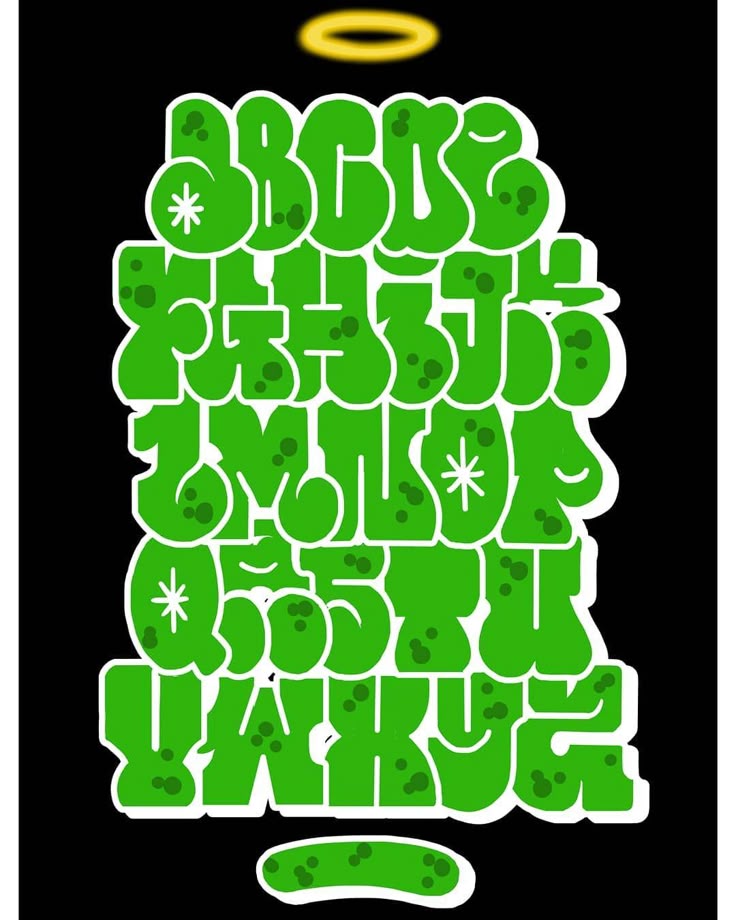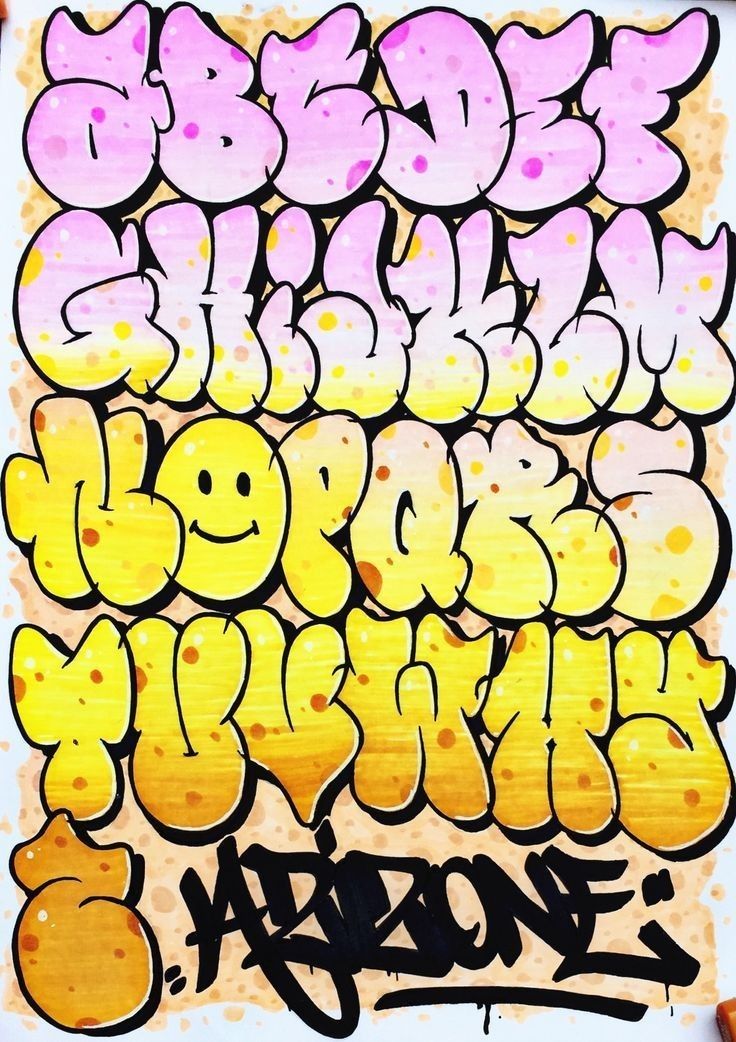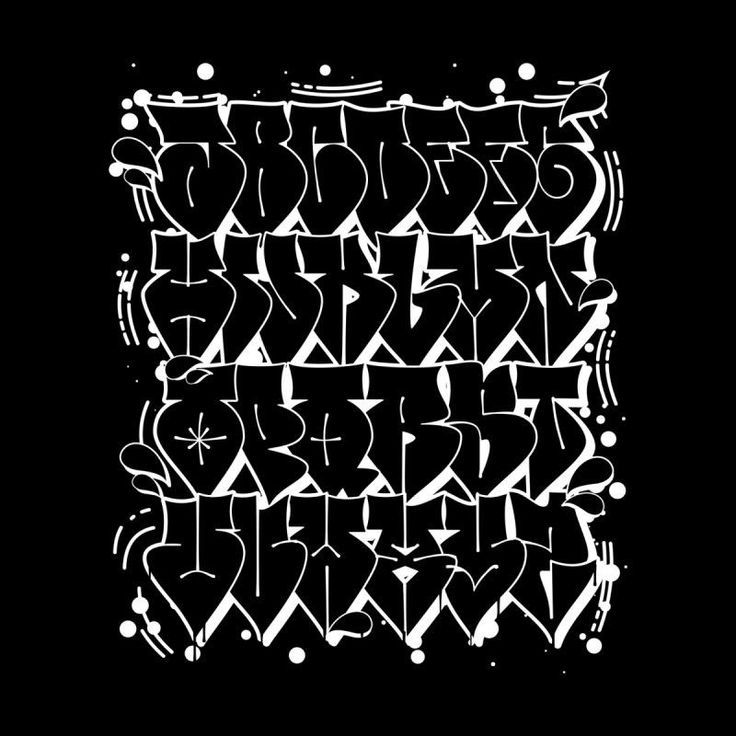
28 лучших шрифтов граффити для городского дизайна
Шрифты граффити идеально подходят для уличного искусства, наклеек и любого другого дизайна, в котором вы пытаетесь создать эклектичную городскую эстетику.
Они мощные, резкие и полные индивидуальности.
Чтобы помочь вам найти идеальный шрифт для ваших проектов в уличном стиле, мы составили список лучших граффити-шрифтов на рынке.
Мы тщательно отобрали этот список и позаботились о том, чтобы в него вошли только самые лучшие шрифты от лучших дизайнеров. Существует сочетание бесплатных и премиальных вариантов, поэтому вы сможете найти то, что соответствует вашему проекту и бюджету.
Что такое граффити-шрифты?
Шрифты Graffiti — это шрифты, вдохновленные уличным искусством. Они дерзкие, громкие и характерные, и обычно выглядят так, как будто их поцарапали, нацарапали или распылили на поверхность.
Существует множество различных типов шрифтов для граффити, но некоторые из самых популярных включают:
- Трафаретные шрифты . Они пытаются воссоздать вид, который вы получите, рисуя граффити распылением по трафарету. Вспомните Бэнкси.
- Накидные купели. Это шрифты, похожие на теги, которые обычно состоят из пузырьковых букв.
- Шрифты Wildstyle . Wildstyle — сложный, замысловатый стиль граффити. Эти типы шрифтов, как правило, трудно читаемы и сильно стилизованы.
- Капающие купели . Этот стиль шрифта граффити имеет формы букв, которые выглядят так, как будто с них капает краска.
- Шрифты кисти . Это шрифты, которые пытаются имитировать мазки кисти
- Начертанные шрифты . Этот тип граффити-шрифта выглядит так, как будто он был грубо и небрежно написан ручкой или карандашом, как если бы вы рисовали в блокноте.
В отличие от других типов шрифтов, шрифты Graffiti не предназначены для чтения. Они чисто художественные. Таким образом, они обычно не являются хорошим выбором для таких вещей, как заголовки или основной текст, но они очень художественны и могут отлично смотреться на плакатах, модных товарах и наклейках.
28 лучших граффити-шрифтов
1. Nightfate — наш лучший выбор
Nightfate, по рисунку, является самым популярным граффити-шрифтом на Envato Elements — и я понимаю, почему.
Он использует жирные, похожие на пузыри символы с сочетанием закругленных краев и острых углов и поставляется в форматах TTF, OTF и WOFF.
Почему это наш лучший выбор
В Nightfate есть все, что мы ищем, в граффити-шрифте. Он использует классический дизайн в стиле броска, который должен быть знаком всем, кто когда-либо жил в городской местности. Это универсальный шрифт, который не будет выглядеть неуместным на уличном искусстве, но также будет хорошо работать в дизайне одежды, настенных украшениях и наклейках, и даже логотипе.
2. Rollover
Rollover — это шрифт для граффити от Vunira. Эффект капель заставляет буквы выглядеть так, как будто они были распылены, а краска все еще влажная. Это также делает этот шрифт хорошим для дизайна на тему ужасов, так как в правильном цвете эффект капания может напомнить кровь.
Это может хорошо работать на обложках книг ужасов, наклейках и кинопостерах. Пакет шрифтов также содержит стилистические варианты, лигатуры и росчерки.
3. Throw-up Font
Вот классный многослойный всплывающий шрифт от дизайнера Гаспера Муньоса. Дизайнер (имеющий опыт граффити) черпал вдохновение в культуре граффити, особенно в «бомбах» и «флопах» — подвидах граффити, которые можно создать быстро и которые известны своими простыми формами.
Флопы и бомбы обычно изготавливаются с помощью аэрозольной краски и клапанов, позволяющих краске переходить от тонких к толстым мазкам, и Гаспер попытался отразить это в своем шрифте. Разве вам не нравятся эти милые округлые формы букв?
Пакет шрифтов поставляется в четырех версиях: обводка, заливка, тень и выделение. Эти различные варианты могут быть наложены друг на друга, чтобы создать привлекательный дизайн, который, кажется, спрыгивает со страницы.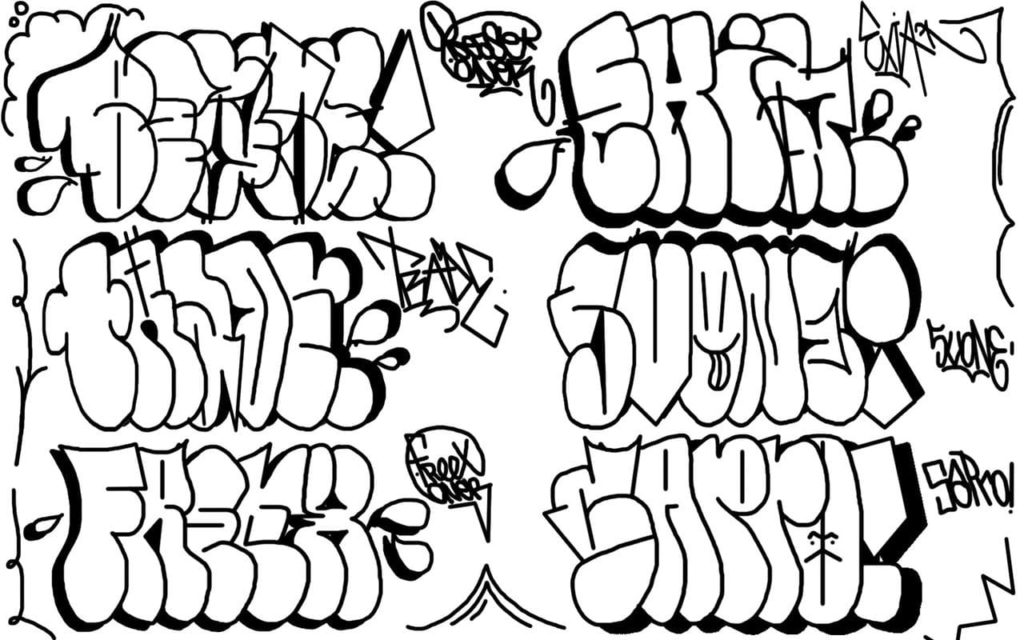
Цена: Бесплатно
Цена: Личное и коммерческое использование включено в подписку на Envato Elements (16,50 долларов США в месяц)
4. Он вдохновлен уличным искусством и напоминает мне о тегах, которые можно увидеть на кирпичной стене. Это будет хорошо работать с дизайном в стиле хип-хоп, уличной одеждой и настенным искусством. Он поставляется с заглавными буквами, знаками препинания и цифрами в формате OTF и TTF.
Цена: Личное и коммерческое использование, включенное в подписку Envato Elements ($16,50/месяц)
5. Luser
Luser — это шрифт современного уличного искусства, вдохновленный культурой хип-хопа и граффити. Он имеет плавные мазки, которые выглядят круто, и это один из самых читаемых граффити-шрифтов в этом списке, поэтому он может хорошо работать в заголовках.
Цена: Личное и коммерческое использование, включенное в подписку на Envato Elements (16,50 долларов США в месяц)
6.
Bombsky
Забудьте о Бэнкси, позвольте представить вам Bombsky — граффити-шрифт от Blankids. Как следует из названия, дизайн основан на классических граффити-бомбах (напоминаем: бомбы — это простые граффити-ярлыки, которые можно быстро сбросить). Я вижу, как это выглядит очень красиво на обложке хип-хоп альбома.
Цена: Личное и коммерческое использование, включенное в подписку Envato Elements ($16,50/месяц)
7. Punk Kid
Освободите свой внутренний панк с помощью этого бесплатного трафаретного шрифта в стиле граффити от Криса Хансена. Punk Kid отличается от других шрифтов, которые мы рассматривали до сих пор, тем, что он использует классический стиль трафарета с аккуратными однородными формами букв. Подобно трафаретным буквам, на лице каждого глифа есть разрывы.
Что отличает Punk Kid от классических трафаретных шрифтов, так это крутая размытая текстура и крапчатый эффект, из-за которых он выглядит так, как будто его небрежно распылили в спешке.
Это очень бунтарский шрифт, который будет отлично смотреться на дизайнах обид, веб-сайтах групп, обложках альбомов, концертных афишах и многом другом.
Этот шрифт широко доступен бесплатно даже для коммерческого использования. Но если вы хотите выразить свою благодарность, дизайнер предлагает вам сделать пожертвование в больницу для коал в Новом Южном Уэльсе.
Цена: Бесплатно
8. Beslyn
Beslyn — изящный, изысканный шрифт в стиле граффити от Skiiler Studio. Элегантный стиль хорошо подходит для более серьезного, профессионального или стильного дизайна и особенно хорошо смотрится на темном фоне. Это встроенный шрифт, что означает, что он имеет тонкую штриховую линию внутри каждой буквы, чтобы добавить контраста и визуального интереса.
Цена: Личное и коммерческое использование, включенное в подписку Envato Elements ($16,50/месяц)
9. Hosp
Hosp — это стильный каллиграфический шрифт от Nick Asphodel Design.
Дизайнер хотел «помочь творческим людям создавать впечатляющие дизайны» и создал Hosp вручную с помощью остроконечной кисти. Наклонные, угловатые формы букв, чернильные пятна и грубые мазки выглядят круто и создают мощную атмосферу. Этот вариант идеально подходит для дерзких дизайнов продуктов, принтов на кепках, наклеек и других городских дизайнов.
Цена: Бесплатно
10. Airneo
Airneo — еще один потрясающий граффити-шрифт, который заставляет меня думать о баскетбольных площадках, кроссовках и хип-хопе. Он использует забавный, интересный и смелый дизайн с интересными завитушками, такими как наконечники стрел на концах перекладин, чтобы добавить изюминку. Он содержит прописные и строчные буквы, цифры, знаки препинания и многоязычные глифы.
Цена: Личное и коммерческое использование, включенное в подписку на Envato Elements (16,50 долларов США в месяц)
11. Mind The Gap
Mind the Gap — еще один трафаретный шрифт, который может хорошо работать в дизайне, вдохновленном уличным искусством и граффити.
Дизайнер был вдохновлен отношениями любви и ненависти, которые у него были с его ежедневными поездками в Лондон (отсюда и название, которое должно быть знакомо всем, кто когда-либо ездил в метро).
Шрифт отражает индустриальный, утилитарный характер станций метро в больших городах. Он был сделан путем ручной вырезки буквенных трафаретов и окраски их распылением. Военный вид компенсируется преднамеренными несовершенствами, которые делают его почти грязным и привносят некоторую индивидуальность в то, что в противном случае было бы относительно скучным дизайном.
Цена: Личное и коммерческое использование, включенное в подписку Envato Elements ($16,50/месяц)
12. Road Rage
Road Rage — агрессивный граффити-шрифт от Youssef Habchi. Острые углы и текстурированные мазки добавляют эффектности и делают этот шрифт одним из самых дерзких в этом списке. Я злюсь, просто глядя на это.
Цена: Бесплатно
13.
Брэдуолл
Далее у нас есть граффити-шрифт Bradwall от Blankids. Тебе не кажется, что на скейтборде это будет выглядеть круто? Опять же, он использует знакомый стиль с округлыми пузырьковыми буквами. Он бывает двух видов: обычный и контурный.
Цена: Личное и коммерческое использование, включенное в подписку на Envato Elements (16,50 долларов США в месяц)
14. Insanity
Insanity — современный шрифт в стиле граффити с собственным уникальным чувством стиля, от TK студия. Дизайнер выбрал более тонкие штрихи вместо пузырьковых букв, которые вы часто видите в шрифтах в стиле броска, что делает этот шрифт немного более универсальным. Это хаотично, дико и чертовски гангстерски. Попробуйте это на своих плакатах, уличных журналах, обложках YouTube, миниатюрах и постах в социальных сетях.
Цена: Личное и коммерческое использование, включенное в подписку Envato Elements ($16,50/месяц)
15.
Шрифт Diediedie
Далее у нас есть кое-что немного другое. Diediedie — это самопровозглашенный «злой каракуль-шрифт, которому определенно нельзя доверять». Вместо мазков кистью или баллончика с краской он имитирует маниакальные, беспорядочные каракули, которые можно делать ручкой в блокноте.
Страшный и немного жестокий, что делает его идеальным шрифтом для ужастиков и обложек альбомов рок-музыки. Помимо всех обычных глифов, дизайнер также включил несколько изящных дингбатов (таких как пентаграмма и череп), которые вы можете использовать, чтобы оживить свои проекты.
Цена: Бесплатно
16. Snakehead
Snakehead — это шрифт, похожий на теги, который будет отлично смотреться в логотипах, уличной одежде, брендинге и других проектах. Это шрифт с заглавными буквами, который содержит буквы от A до Z, цифры и знаки препинания, а также различные альтернативы и росчерки.
Цена: Личное и коммерческое использование, включенное в подписку на Envato Elements (16,50 долларов в месяц)
17. Flim Flom
Наполните свои проекты эстетикой ручной работы с Flim Flom от Maulana Creative. Это очень декоративный шрифт, который выглядит так, будто его нарисовали маркером или фломастером. Небольшие штрихи, такие как замена названия букв, таких как i и j, крестиками, добавляют визуального интереса и делают этот шрифт одним из самых оригинальных в этом списке.
Цена: Личное и коммерческое использование, включенное в подписку на Envato Elements (16,50 долларов в месяц)
18. Degrassi Font
Degrassi — это дурацкий шрифт, вдохновленный граффити, с волнистыми линиями и штрихами, заканчивающимися наконечниками стрел. Он доступен бесплатно и хорошо подходит для игровой графики, футболок, логотипов, постеров и многого другого.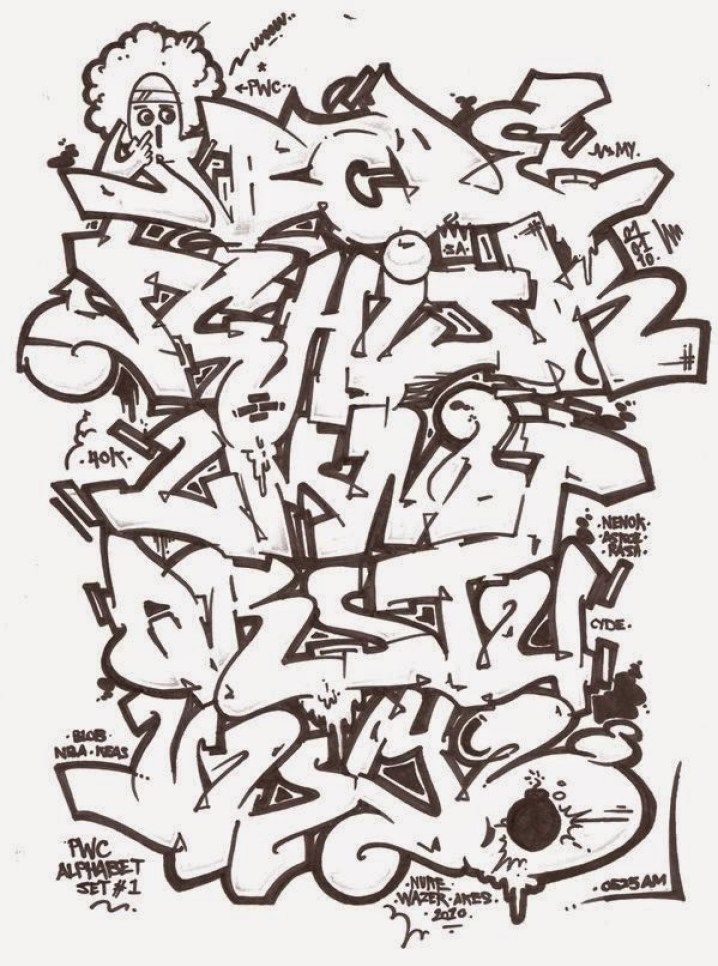
Цена: Бесплатно
19. MWD Graff
MWD Graff — шрифт для граффити в диком стиле от Priority Type Co. В истинно диком стиле он отличается замысловатыми, сложными штрихами и очень детализирован. Это не самый читаемый шрифт в этом списке, но он очень художественный. Он поставляется в двух стилях: базовый и экструдированный. Вы можете добавить вытянутую версию позади обычной версии в качестве слоя для создания 3D-эффекта.
Цена: Личное и коммерческое использование, включенное в подписку Envato Elements ($16,50/месяц)
20. Fillings Urban
Fillings Urban — крупный шрифт в стиле граффити, вдохновленный молодежной культурой. Для него характерны изогнутые формы букв, толстые штрихи и счетчики, похожие на кресты. Он выглядит немного мультяшным и может хорошо работать в комиксах и мультфильмах, а также в городском, уличном дизайне.
Цена: Личное и коммерческое использование включено в подписку Envato Elements (16,50 долларов США в месяц)
21.
Шрифт граффити
Шрифт Майка Каролоса с метким названием «граффити-шрифт» забавный и игривый. Он выглядит не так агрессивно, как некоторые другие шрифты в этом списке, и может хорошо работать в дизайне, ориентированном на детей, например, на обложки детских книг, мобильные игры и упаковку игрушек.
Цена: Бесплатно
22. Улица Городская
Street Urban — еще один забавный и смелый шрифт, вдохновленный граффити. Он отлично смотрится в ярких, ярких цветах и, как и последний шрифт, идеально подходит для детского дизайна, такого как детские плакаты и обложки книг.
Цена: Личное и коммерческое использование, включенное в подписку на Envato Elements ($16,50/месяц)
23. Bowings
Bowings — высокий жирный граффити-шрифт с забавной темой. Он отлично подходит для мультфильмов, комиксов, наклеек и настенных рисунков.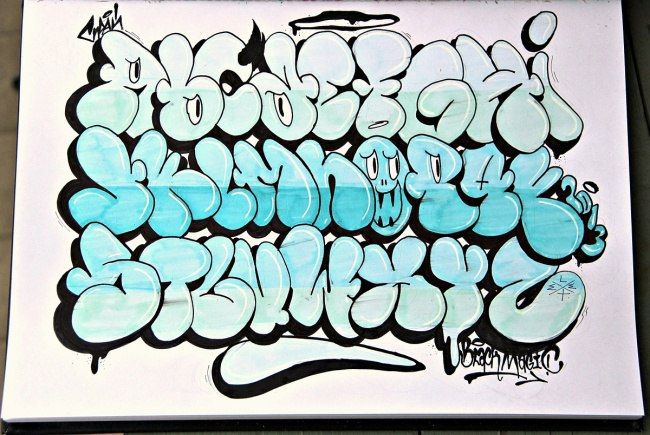
Цена: Личное и коммерческое использование включено в подписку Envato Elements ($16,50/месяц)
24. Autobahn
Autobahn (автомагистраль по-немецки) — еще один трафаретный шрифт с большим количеством деталей. Он очень похож на Mind The Gap, но с несколькими штрихами, которые придают ему уникальный стиль. Это не традиционный векторный шрифт, вместо этого он использует новый формат OpenType SVG, поэтому он такой реалистичный и подробный.
Цена: Личное и коммерческое использование, включенное в подписку Envato Elements ($16,50/месяц)
25. Free Graffiti Front
Если вы ищете уникальный шрифт для граффити, который вы можете использовать бесплатно, это оно. Он имеет дизайн в стиле дикого стиля с волнистыми буквами, которые трудно читать, поэтому он не будет хорошо работать в основном тексте, но идеально подходит для дисплеев.
Цена: Бесплатно
26.
Незуко
Nezuko — причудливый шрифт с острыми углами и без каких-либо изгибов. Это не традиционный шрифт для граффити, но он включает в себя некоторые элементы, характерные для этого стиля. Это очень эстетично и может отлично смотреться в названиях инди-игр, обложках книг и кинопостерах.
Цена: Личное и коммерческое использование, включенное в подписку на Envato Elements ($16,50/месяц)
27. Dirty Lizard
Dirty Lizard — еще один шрифт для граффити в стиле тегов, который станет хорошим дополнением к широкому кругу дизайнерских проектов. Он может работать со всем, от логотипов и этикеток до дизайна одежды и заголовков.
Цена: Личное и коммерческое использование, включенное в подписку Envato Elements ($16,50/месяц)
28. Wall Painter
И последнее, но не менее важное: у нас есть Wall Painter — шрифт грубой кисти от Tokopress.
В отличие от большинства других граффити-шрифтов, этот не имеет эффекта распыления. Создается впечатление, будто дизайнер рисовал широкими мазками. Он идеально подходит для бунтарского дизайна, такого как плакаты протеста, музыкальные плакаты, резкие посты в социальных сетях и музыкальные журналы.
Цена: Личное и коммерческое использование, включенное в подписку на Envato Elements (16,50 долларов в месяц)
Как выбрать шрифт для граффити
Как видите, существует множество шрифтов для граффити на выбор — так как вы выбираете правильный для вашего проекта ? Что ж, вот несколько факторов, о которых стоит подумать, взвешивая варианты:
- Стиль. Шрифты Graffiti бывают самых разных форм и стилей, таких как дикий стиль, вбрасывание, трафарет и т. д. Попробуйте выбрать тот, который соответствует эстетике вашего произведения искусства или дизайнерского проекта.
- Совместимость с вашим программным обеспечением для проектирования.
Обязательно выберите шрифт, который будет работать с используемым вами программным обеспечением для дизайна. Некоторые расширения файлов (например, цветные шрифты SVG) могут работать только с Photoshop и Illustrator и т. д. - Лицензия. Многие из бесплатных шрифтов в этом списке бесплатны только для личного использования. Если вы планируете использовать свой граффити-шрифт для коммерческого или рекламного проекта, вам может потребоваться приобрести лицензию. Убедитесь, что вы прочитали мелкий шрифт, чтобы быть уверенным.
Мы надеемся, что вы нашли это полезным. Удачи!
24 фантастических бесплатных шрифта для граффити в 2022 году
(Изображение предоставлено Майком Каролосом)
Лучшие бесплатные шрифты для граффити могут добавить уличного стиля любому дизайну. Граффити существует во многих стилях, как и лучшие бесплатные шрифты для граффити, а это означает, что вы должны быть в состоянии найти вариант независимо от того, к какому эффекту вы стремитесь, от ярких цветов, которые создают ощущение духа сообщества, до более резкого, бунтарское чувство.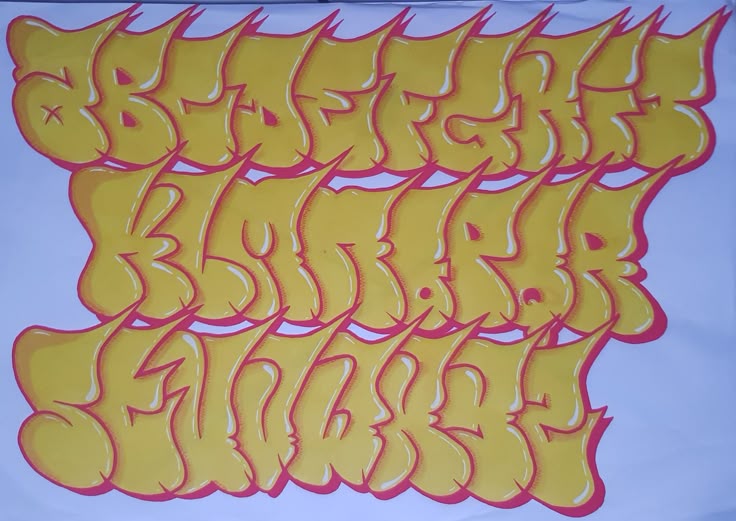
Граффити может ассоциироваться с ненормативной лексикой и вандализмом, а также с сильным творческим духом. И уличное искусство стало настолько вдохновляющим, что его влияние можно ощутить на самых разных носителях, от рекламы до оформления альбомов. Лучшие бесплатные шрифты для граффити могут позволить вам использовать это, но их может быть трудно отследить среди огромного архива шрифтов, доступных для загрузки в Интернете. Вот почему мы составили свой собственный выбор с прямыми ссылками на то, где вы можете их найти, от шрифтов с аэрозольной краской до ручек-кистей и трафаретов.
Как всегда, убедитесь, что вы перепроверили положения и условия, прежде чем использовать какие-либо шрифты для своих проектов. Не все из перечисленных ниже шрифтов бесплатны для коммерческого использования. Если вы не можете найти то, что ищете, не сдавайтесь. У нас есть несколько других отличных бесплатных шрифтов, от лучших бесплатных шрифтов в целом до лучших бесплатных скриптовых шрифтов.
А если вы ищете вдохновения, взгляните на нашу подборку лучших примеров уличного искусства? У нас также есть функции о том, как привнести энергию граффити в типографику, и лучшие бесплатные обои для любителей типографики.
Лучшие бесплатные шрифты для граффити. Он имеет более 130 000 шрифтов, от шрифтов кисти до шрифтов дисплея, и более 900 из них совершенно бесплатны.
01. Rusto Fat Cap Brush
Сообществу Behance нравится этот неоновый шрифт (Изображение предоставлено Luis Di Lascio/Patri Pérez)
- Загрузите Rusto Fat Cap Brush из DropBox (открывается в новой вкладке)
Разработанный Луисом Ди Лашио (открывается в новой вкладке) и Патри Перес (открывается в новой вкладке), Rusto Fat Cap Brush — это забавный и смелый шрифт с аутентичным ощущением граффити. Основанный на самодельной швабре для граффити, этот шрифт идеально подходит для придания проекту молодежной или городской атмосферы.
02. Sprite
Sprite — разборчивый и доступный бесплатный шрифт для граффити (Изображение предоставлено FontFabric)
- Загрузите Sprite из FontFabric (открывается в новой вкладке)
Sprite — это функциональный бесплатный шрифт для граффити, преимущество которого заключается в том, что он хорошо читается, сохраняя при этом ощущение граффити в стиле мазка.
Созданный для широкой аудитории, он предлагает доступный способ добавить городскую черту вашему проекту.
03. Urban Decay
В Urban Decay есть все, что вам нужно, от современного бесплатного граффити-шрифта (Изображение предоставлено Zofos на DaFont)0039
Городской распад — это шрифт ручной работы, созданный кистью, созданный создателем Zofos, чтобы «прославить граффити, городские исследования, уличную каллиграфию и жизнь в центре города». Этот шрифт является одним из лучших шрифтов для граффити, которые мы видели, с грубой аутентичностью, которая привнесет городскую атмосферу в ваши проекты. Скачать можно бесплатно, но пожертвования приветствуются.
04. Philly Sans
Philly Sans — это универсальный шрифт с граффити (Изображение предоставлено: Philatype на 1001Fonts)
- Загрузите Philly Sands с DaFont (открывается в новой вкладке)
Тяжелый шрифт, состоящий только из строчных букв, который напоминает граффити, а также очень четкий для чтения, Philly Sans, безусловно, универсален.
Созданный Philatype, это отличный шрифт для отображения. Это бесплатно для личного использования.
05. Шрифт The Graffiti
Этот ручной шрифт представляет собой граффити во всей красе (Изображение предоставлено Mike Carolos)
- Загрузите шрифт Graffiti из DropBox яркий удар. Созданный графическим дизайнером Майком Каролосом (открывается в новой вкладке), этот шрифт абсолютно бесплатен, но доступен только в формате png (он не набирается клавишами). Он также поставляется в черно-белом варианте.
06. Knight Brush
Knight Brush — адаптируемая и жирная кисть с реалистичными мазками (Изображение предоставлено Hendra Pratama на FreeFonts) В эпоху граффити Хендра Пратама создал этот бесплатный граффити-шрифт, ориентируясь на нарисованные вручную вывески. Этот адаптируемый шрифт напоминает настоящие мазки кисти и является смелым выбором. Бесплатная версия представляет собой демо-версию только для личного использования, но вы можете скачать полную коммерческую версию за 15 долларов.
07. Fat Wandals
Получите наконечник долота (Изображение предоставлено Mans Greback на DaFont) в новой вкладке) — это бесплатная версия семейства шрифтов Wandals, предназначенная только для личного использования. Это великолепно выглядящий рукописный шрифт с красивыми плавными штрихами, которые выглядят так, будто они были сделаны маркером с наконечником долота, и он поставляется с полным набором символов с множеством вариантов и всеми знаками препинания, которые вам могут понадобиться.
08. Граффити Дона
Граффити Дона приятно урбанистично, но имеет дружелюбную атмосферу (Изображение предоставлено Доном Марчиано на DaFont) (открывается в новой вкладке), Don Graffiti — это бесплатный шрифт для граффити старой школы, который идеально подходит для придания любому проекту особого урбанистического колорита. Это шрифт с заглавными буквами, который поставляется в виде файла OTF, содержащего 197 глифов с вариантами, цифрами и пунктуацией.
09.
Атака гризлиЗаймитесь гризли (Изображение предоставлено Rometheme на DaFont)
- Загрузите Атака гризли от DaFont (откроется в новой вкладке)
Если медведи гризли решили попробовать свои лапы царапая когтями прямо по стене, тогда это могло бы выглядеть примерно так, как этот поразительный рукописный шрифт от Rometheme. Все заглавные, с цифрами и приличным набором дополнительных символов.
10. Трафарет для щелей
Crevice Stencil резкий, но элегантный (Изображение предоставлено: Checkered Ink на FontSpace) Crevice Stencil — это бесплатный шрифт, созданный для сообщества дизайнерской студией Bath Checkered Ink. Вы можете использовать этот шрифт бесплатно в личных проектах, но если вы хотите использовать его в коммерческих целях, вам необходимо приобрести лицензию.
11. Mersey Cowboy
Запутайтесь с Mersey Cowboy. более тесно связан с брызгами на граффити. Mersey Cowboy — один из лучших бесплатных граффити-шрифтов, если вы хотите, чтобы ваш шрифт выглядел беспорядочно и хаотично, но при этом хорошо читался.
Опять же, этот граффити-шрифт бесплатен для личного использования, но вам нужно будет заплатить за лицензию, чтобы использовать его в коммерческих целях.12. Nebulous
Nebulous использует гранжевой подход к типографике в стиле трафарета (Изображение предоставлено: Highlight on FontSpace) это привносит нотку проблемного научно-фантастического шика в категорию трафаретных шрифтов. Этот шрифт, созданный бразильским дизайнером Побренердом, бесплатен как для личного, так и для коммерческого использования.
13. Sloppy Paint
Бесплатный граффити-шрифт Sloppy Paint флуоресцентный, забавный и совершенно потрясающий (Изображение предоставлено Darrell Flood on FontSpace)
- Загрузить Sloppy Paint из Font Space (откроется в новой вкладке)
Sloppy Paint выглядит именно так, как кажется, изобилует счастливыми яркими цветами и жирными мультяшными формами. Этот граффити-шрифт, созданный японским геймдизайнером Дарреллом Фладом, также известным как «dadimouse» (открывается в новой вкладке), можно бесплатно загрузить для личного использования.
Flood просит пожертвовать минимум 10 долларов на коммерческое использование.14. Thickedy Grunge
Thickedy Grunge бесплатен только для личного использования (Изображение предоставлено: Checkered Ink на FontSpace)
- Загрузите Thickedy Grunge из Font Space (открывается в новой вкладке)
Это еще один отличный бесплатный граффити-шрифт, который выглядит точно так, как предполагает его название. Это еще один дизайн от дизайнерской студии Bath Checkered Ink. Опять же, это бесплатно для личного использования, но если вы хотите использовать его для коммерческого проекта, вам нужно будет купить лицензию.
15. Fibre
Текстовое волокно, состоящее из заглавных букв, естественное и аутентичное, но при этом легко читаемое (Изображение предоставлено WildOnes Design)
- Загрузить Fiber с сайта WildPicks (откроется в новой вкладке)
Fiber — это рукописный шрифт, написанный только заглавными буквами, с диким и царапающим ощущением.
В то же время показатели кернинга и шрифта были разработаны для обеспечения чистого и легкого чтения, поэтому стиль не имеет значения по содержанию. Этот шрифт, созданный латвийской студией Wild Ones Design (открывается в новой вкладке), является бесплатным для личного использования в обмен на ваш адрес электронной почты.16. Metro Grunge
Metro Grunge бурлит энергией DIY (Изображение предоставлено Peter Olexa, DaFont)
- Скачать Metro Grunge от DaFont (открывается в новой вкладке)
Metro Grunge — это бесплатный шрифт от Peter Olexa, внештатного дизайнера из Братиславы, Словакия. Этот шрифт, наполненный энергией андеграунда (как метафорической, так и реальной), бесплатен как для личного, так и для коммерческого использования.
17. Humblle Rough
У Humble Rough есть восхитительное чувство дисбаланса (Изображение предоставлено Dirtyline Studios)0017 (открывается в новой вкладке)
Humblle Rough — это рукописный шрифт с кистью в пьянящем уличном стиле.
Этот бесплатный граффити-шрифт имеет несовершенный набросок от руки. Это еще один шрифт, созданный Dirtyline Studios, и его можно бесплатно загрузить только для личного использования.
18. Витрувианский человек
Витрувианский человек представляет собой нарисованные каракули в самом первобытном виде (Изображение предоставлено: Checkered Ink на FontSpace)
- Загрузить Витрувианский человек из Font Space (открывается в новой вкладке)
Этот шрифт дикий, дикий, дикий: если вы хотите подчеркнуть злобную, вандалистскую сторону культуры граффити, Vitruvian Man вполне может стать отличным выбором. Этот шрифт, разработанный Checkered Ink, бесплатен только для личного использования.
19. Sister Spray
Sister Spray от ImageX невероятно грязный (Изображение предоставлено: Imagex on DaFont) , опять же от ImageX. Он состоит из полного набора заглавных букв, нарисованных аэрозольной краской, плюс пара строчных букв для акцента, а также несколько брызг, пятен и штрихов для завершения образа.
Это бесплатно для личного использования; свяжитесь с ImageX, если вы хотите использовать его в коммерческих целях.
20. Тип тега
Графический дизайнер Энди Панченко был вдохновлен тегами граффити при создании этого оригинального дизайна (Изображение предоставлено Энди Панченко) ищете стиль, используемый в тегах граффити, это может быть один из лучших шрифтов граффити для вашего проекта. Граффити-шрифт Tag Type был создан графическим дизайнером Энди Панченко. Студенческий проект, дизайн Панченко был вдохновлен тегами граффити, которые он видел на улицах. Это бесплатно для личного использования.
21. Blow Brush
Blow Brush — рукописный маркерный шрифт, вдохновленный культурой хип-хопа и сообществом граффити (Изображение предоставлено Петаром Акански)
Дизайнер и разработчик внешнего интерфейса Петар Акански создал этот смелый, причудливый граффити-шрифт Blow Brush. «Blow Brush — это шрифт в стиле рукописного маркера, вдохновленный культурой хип-хопа и сообществом граффити», — комментирует Акански на Behance.
«Несмотря на то, что основной целью было привнести этот уличный стиль в ваш контент, важность функциональности шрифта была главным приоритетом. Результатом являются разборчивые буквы, четкий шрифт, множество вариаций и шрифт, полезный для более широкой аудитории. »
22. Gang Bang Crime
Этот шрифт идеально подходит для добавления нотки стилизованного уличного чванства к вашим фотографиям в метро (Изображение предоставлено Maelle Keita)
Дизайнер Маэль Кейта предлагает два набора этого шрифта для граффити без заглавных букв, один с капающей краской, а другой без нее. Он предлагает отличный стиль граффити в стиле метро. Этот шрифт бесплатен только для личного использования.
23. Полла
Polla — это живой шрифт кисти, наполненный пятнами и брызгами (Изображение предоставлено Юхой Корхонен на сайте 1001Fonts). новая вкладка), Polla — это удивительно грязный шрифт кисти, наполненный пятнами и брызгами, которые действительно оживят ваш текст.
Это бесплатно для личного использования, и если вы хотите использовать его в коммерческих целях, это будет стоить вам всего 15 евро / 20 долларов.
24. Damsterdam
Смелые кривые буквы Дамстердама наполнены энергией (Изображение предоставлено Junkohanhero on Fonts) Тяжелый шрифт с заглавными буквами, сделанный толстыми, грубыми мазками кисти, с кривыми, ступенчатыми формами букв, которые просто полны энергии. Как и в случае с Polla, это 15 евро / 20 долларов США для коммерческого использования, но бесплатно для личных проектов.
Подробнее:
- Лучшие бесплатные кисти
- Лучшие книги по графическому дизайну
- Лучшее программное обеспечение для графического дизайна
Спасибо, что прочитали 5 статей в этом месяце* Присоединяйтесь и получите неограниченный доступ
Наслаждайтесь первым месяцем всего за 1 фунт стерлингов / 1 доллар США / 1 евро
У вас уже есть аккаунт? Войдите здесь
*Читайте 5 бесплатных статей в месяц без подписки
Присоединяйтесь, чтобы получить неограниченный доступ
Попробуйте первый месяц всего за 1 фунт стерлингов / 1 доллар США / 1 евро
У вас уже есть аккаунт? Войдите здесь
Джо — постоянный журналист-фрилансер и редактор Creative Bloq.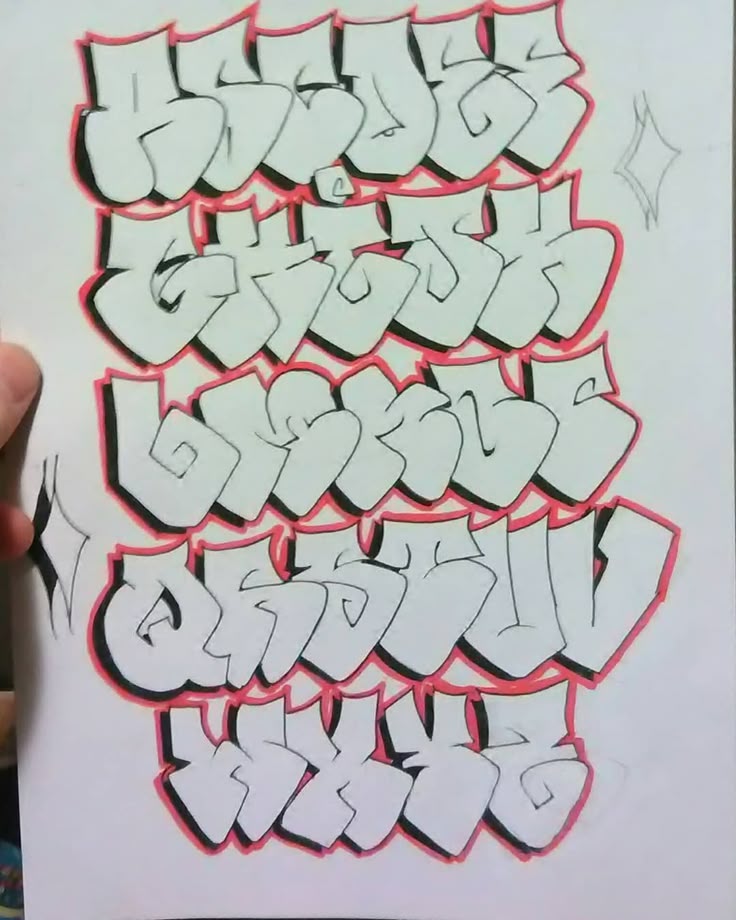
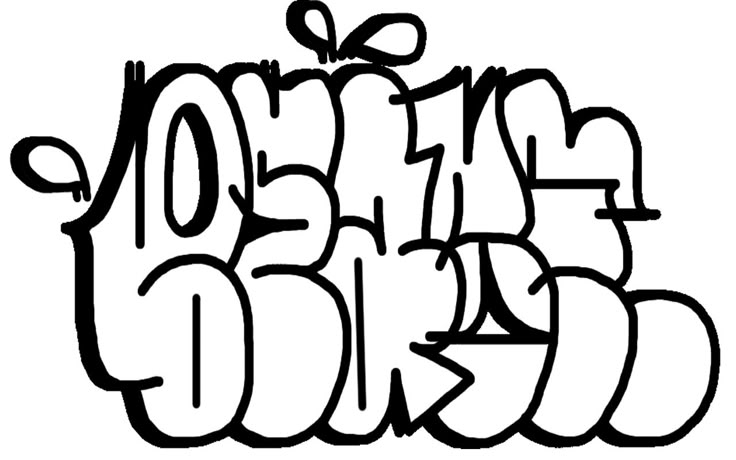
Обязательно выберите шрифт, который будет работать с используемым вами программным обеспечением для дизайна. Некоторые расширения файлов (например, цветные шрифты SVG) могут работать только с Photoshop и Illustrator и т. д.
Атака гризли
Опять же, этот граффити-шрифт бесплатен для личного использования, но вам нужно будет заплатить за лицензию, чтобы использовать его в коммерческих целях.
В то же время показатели кернинга и шрифта были разработаны для обеспечения чистого и легкого чтения, поэтому стиль не имеет значения по содержанию. Этот шрифт, созданный латвийской студией Wild Ones Design (открывается в новой вкладке), является бесплатным для личного использования в обмен на ваш адрес электронной почты.